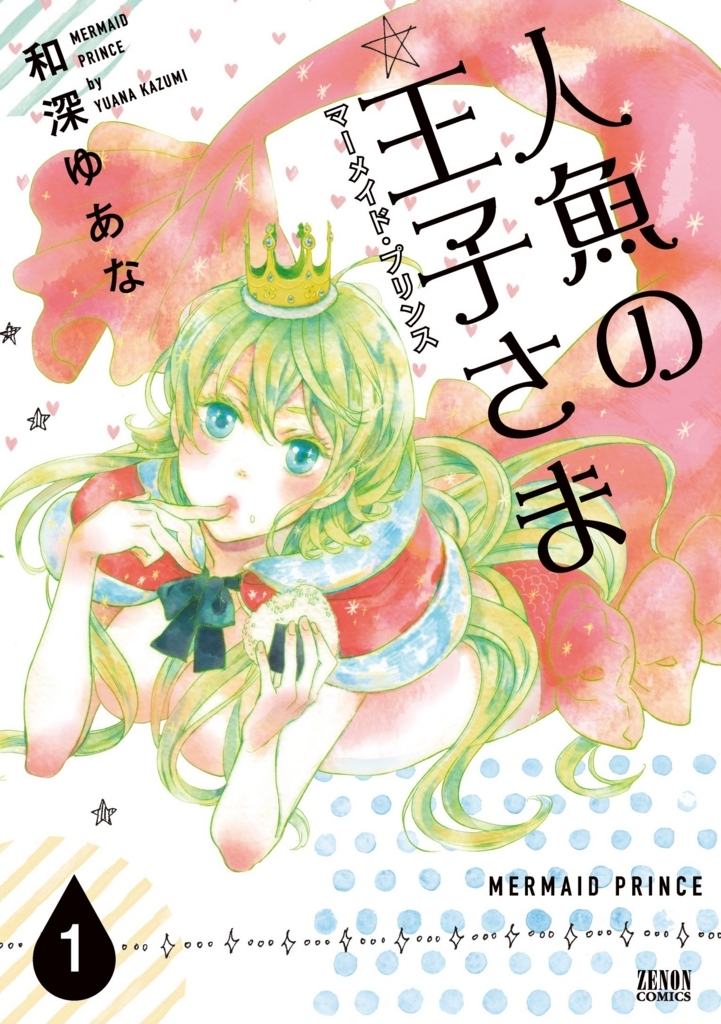
人魚の王子さま
和深ゆあな氏に著書による恋がしたい人魚(人間の姿では男)×人魚に恋した男という中身は純愛、見た目はボーイズラブのトランスセクシャル・ラブ・コメディ。
和深ゆあなProfile●「だから金田は恋ができない」(ARIA)「ハルハナ」「カチンコ」「惑星ドロップス」(ASUKA)など。人魚の王子さまが青年誌初連載。
人魚の王子さまのタイトルのフォントとして優雅宋が採用
ゼノンコミックス「人魚の王子さま」のタイトルにダイナフォントの優雅宋が一部加工されて採用されている。
優雅宋
細い横線と太い直線で構成され、ストロークの先端と末端に欧文書体の花文字のような装飾が施されているのが特徴的な書体。古典的な洋風感があり、ロゴ・POP・タイトル・キャッチコピー・看板等、様々な場面で活用されている。